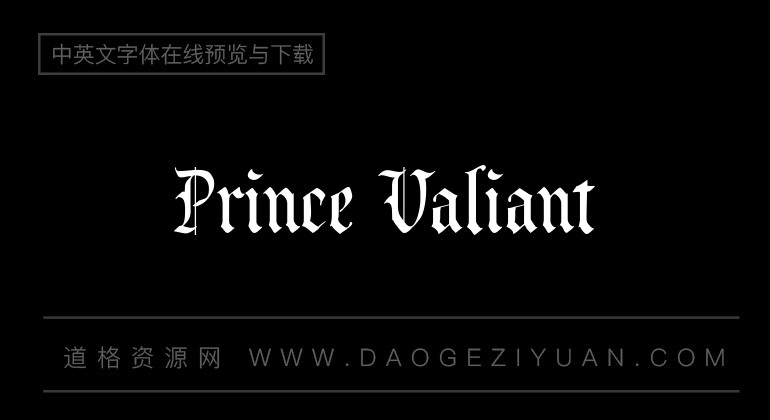
? Prince Valiant 字体是一款经典的英文字体,由美国设计师马克·贝克(Mark Batty)设计,于1937年首次发行。它是一款细长、英式古典风格的字体,常用于书籍、报纸和杂志的标题和封面。Prince Valiant 字体的特点是它的英式古典风格,有着优雅的线条,易于阅读,而且字体的大小可以调整,使它适合不同的应用场景。内容介绍
Prince Valiant是一款非常不错的手写艺术字体,具有很好的视觉感,适合于文化类的宣传设计、商业类品牌的广告和产品包装设计以及个性化文字排版等较多场景。